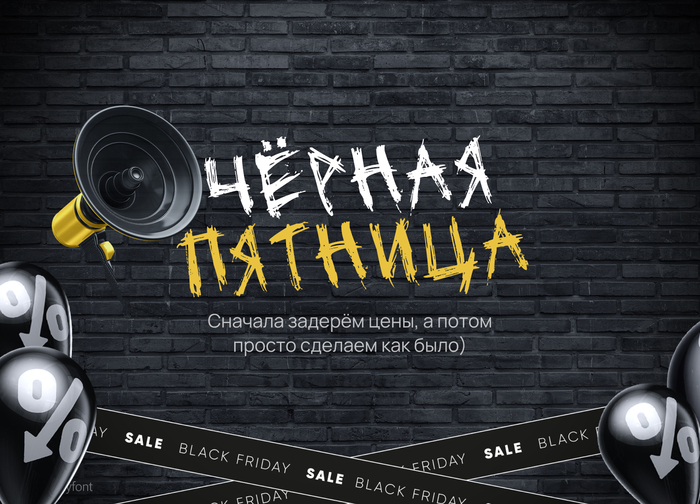
Шрифт Blackcraft. Кириллица
Blackcraft. Дерзкий, как пуля резкий, декоративный шрифт для крупных заголовков. Автор: GGBot. Бесплатно для личного и коммерческого использования.